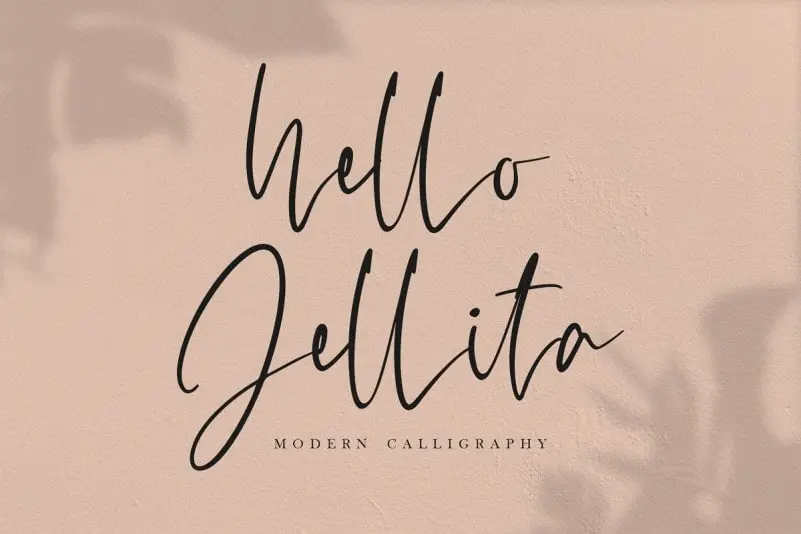
Hello Jellita Script Font – Download Grátis
Bem-vindo ao Hello Jellita Script Font! Esta é uma fonte script com estilo de assinatura escrita à mão. O taniya relly foi criado usando um pincel pen autêntico que imita a escrita à mão. É uma font natural e perfeita para uso em logotipos, convites, embalagens de estação, designs de casamento, postagens nas redes sociais, anúncios, embalagens dos produtos, etiquetas, fotografia, marca d’água e eventos especiais ou qualquer outro lugar. Nossa fonte é uma escolha ideal para quem busca estilo elegante e autêntico em seus projetos digitais. Descubra como essa font pode transformar suas criações!